コーポレートフォントとブランディングフォント
株式会社TBSホールディングス/株式会社TBSテレビ
デザインセンターは、TBSの社内クリエイティブ部門で今回のブランディングに関する多くのデザインを担当しました。デザインセンターではロゴを始めとした番組デザイン、宣伝プロモーション、イベント、動画制作、社内資料、そして印刷物など、扱うデザインの範囲は多岐に渡ります。TBSでは、地上波やBS放送、ラジオ放送などのグループ会社ごと、サービスごとに異なるデザインのロゴを使用していましたが、今回のリブランディングを機に、ひとつのTBSブランドとして見せるため統一したロゴデザインを行うことにしました。同時に、社内資料や番組テロップなどのデザインも同じ見え方にしたいという希望がありました。
ロゴを作ることを目的としたフォントにはグラフィカルな要素が求められます。一方、資料や長文に使うフォントは読みやすさを重視する必要があります。TBSでは、このふたつの目的のために、ブランディング用のカスタムフォントとコーポレートフォントの導入を決め、それぞれ別の視点で選定しました。
コーポレートフォント
デザインセンター デザインマネジメント部
團野慎太郎氏
「たとえばディレクターなどデザイナーではない人が作る資料が同じ見え方になればと思っていました。それと、資料やテロップ、webサイトやデジタルサイネージなどのいろいろな媒体で統一感を持たせたいということもありました。今回、コーポレートフォントとして選ぶにあたり、より見やすく、デザインが洗練されつつも優しい印象という視点でAXIS Fontが良いと思いました。そして、AXIS Fontに合う明朝体も必要でした。」と、デザインセンター デザインマネジメント部の團野慎太郎氏は語ります。
こうして、AXISフィットフォントとTP明朝フィットフォントから、コーポレートフォントとして最適な数値のフォントが選ばれました。現在、TBSのコーポレートフォントとして「TBSゴシック TP」と「TBS明朝 TP」のそれぞれ2ウエイトが約3,700人のグループ社員のパソコンにプリインストールされ、社員用としてデザインセンターが提供するMicrosoft PowerPointやMicrosoft Wordのテンプレートでは「TBSゴシック TP」または「TBS明朝 TP」が使用フォントとして設定されています。
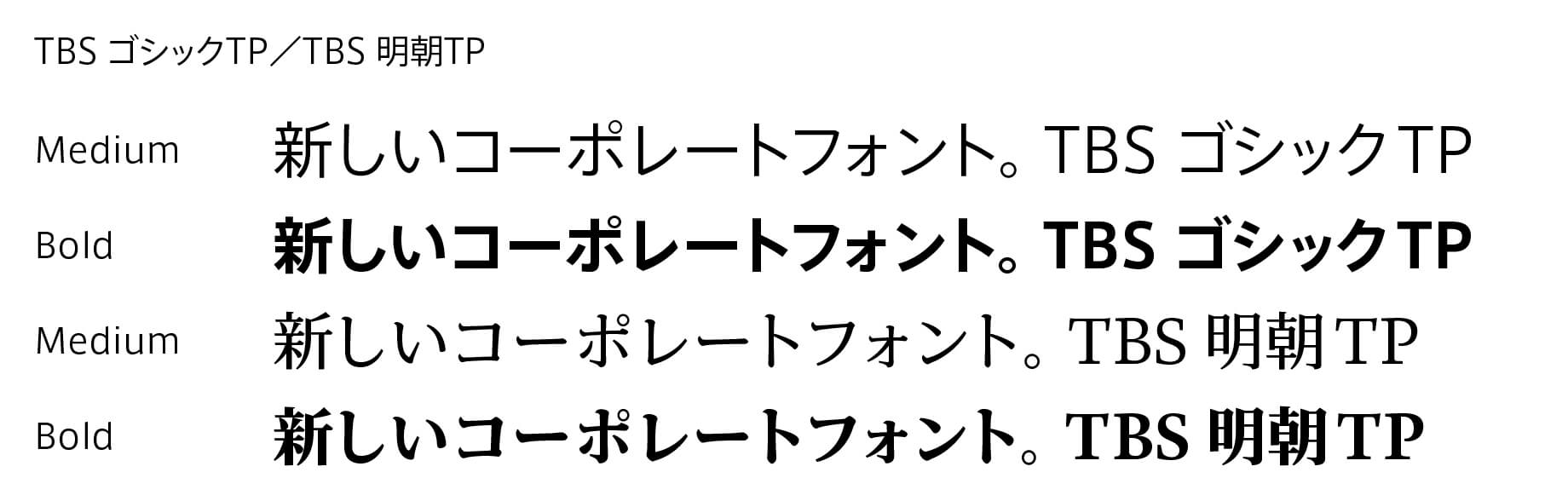
総合プロモーションセンター兼デザインセンターの松原貴明氏は、「TBSでドキュメントを作るときの推奨フォントとしているのですが、その使用が徐々にではありますが増えてきていると実感しています。会社としてコーポレートフォントの導入は初めてなのですが、トーン&マナーを合わせるだけではなく、『フォントを統一することで会社の見え方が変わる』『TBSと名のつくオフィシャルなフォントがあることで、外向きの見え方が統一されていく』など、コーポレートフォントを使うことの意味が理解され始めていると感じています。」と語ります。
コーポレートフォントは、名刺、局内の看板、営業資料、投資家向け冊子などですでに使用が開始されています。また、Webサイトの会社情報ページと社内イントラサイト、ニュース動画配信、そして地上波の報道番組のテロップとしても使用されています。特にテロップでの使用は、デザインの統一感と合わせて、フォント選定というコスト面でも報道局から頼られていると言います。
総合プロモーションセンター部 次長 兼
デザインセンターデザインマネジメント部
松原貴明氏
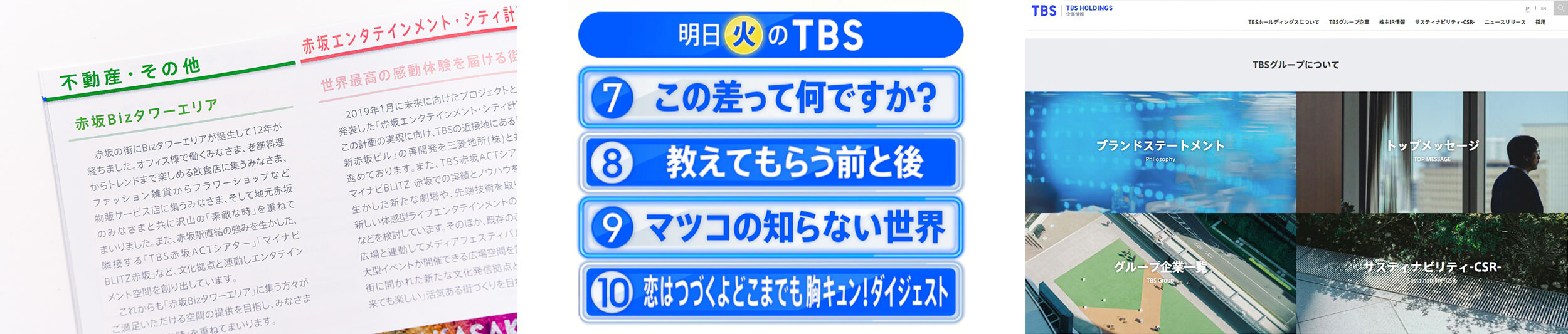
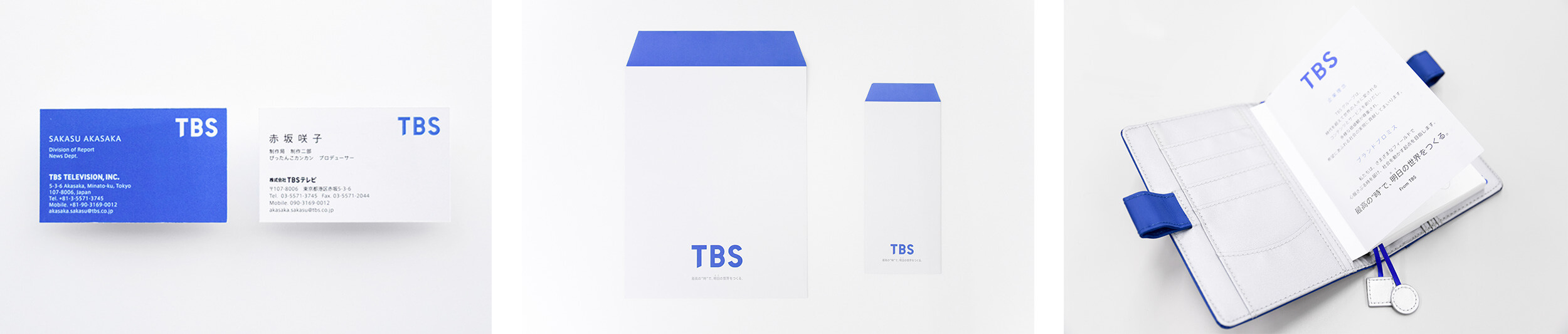
「見え方がより安定してきたということと、書体を毎回選ぶ必要がなくなったことがコスト削減に繋がっています。報道番組は、朝から夜までいろいろな番組があるのですが、フォントによってデザインがバラけてしまうことがよくありました。それが、放送とWebで同じ見え方にできるのは、想定以上の効果です。リブランディングでTBSの青色を規定したこともあって、『ここはTBSのフォントで、TBSの青で』と多くの人が考えるようになり、デザインに対する意識が高まってきたと感じています。想定していた以上に細かなところでコーポレートフォントが使われているのに気づいて、こんなところまで……と感心しています。社内からは、とても読みやすいという声が届いています。」(團野慎太郎氏)
ブランディングフォント
TBSデザインセンターでは、TBSの新しいロゴタイプの仲間となるようなフォントをデザインすること、さらに日本語フォントと組み合わせてブランディング用フォントとして完成させる必要を感じていた際に、フィットフォントと出会ったと言います。
「グループ会社やいろいろなサービスのロゴを同じデザインにしたい、それを誰が作っても同じになるようにしたいと思っていましたので、ロゴを作ることを目的としたオリジナルフォントの開発を考えました。ある講演でタイププロジェクトの話を聞き、オリジナルの欧文フォントが作れるということ、フィットフォントで日本語部分をぴったり合わせてもらえるということを知りました。」(團野慎太郎氏)
原型となるオリジナルデザインの印象を損なわないこと、入力するだけでロゴ作成ができること、そして可読性という機能を備えていることなど、ブランディングフォントの開発にあたりいくつかの条件がありました。日本語部分に関しては、オリジナルの欧文フォントと相性が良いこと、記号類やウエイトが充実していることも重要な点でした。
タイププロジェクトは、欧文フォントを新規開発し、和文部はAXISフィットフォントで最適な数値を設定したブランディングフォント、「TBS Sans TP」の6ウエイトも提供しています。
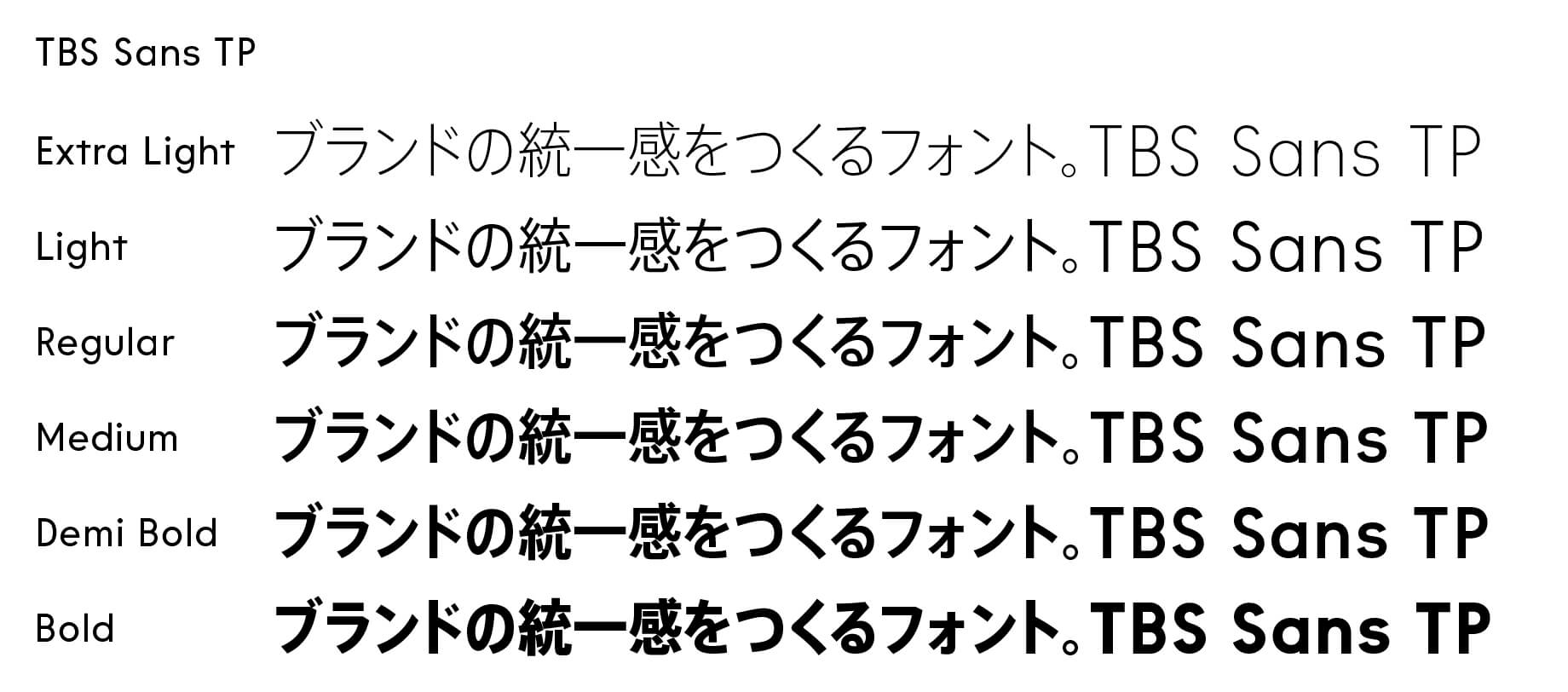
「オリジナル欧文フォントを最初に見た時は、少し驚きました。デザインの原型を渡す時に、ある程度完成しているつもりでしたが、細かいところを修正いただいたことで、フォントとして完成していなかったことに気づきました。実際に使い始めると、入力するだけですぐにロゴとして使える機能性に感動して、何にでも使えるという手応えを感じました。」(團野慎太郎氏)
ブランディングフォントである「TBS Sans TP」は、TBSの新ブランドプロミス「最高の“時”で、明日
の世界を作る」のコピービジュアルを始め、番宣CMやグループ会社や各サービスのロゴなど、あらゆる場面で使用されています。デザイナーチームでは、使用するフォントを検討する必要がなくなったことで、とても効率的に進めることができ、誰が担当してもデザインにブレがないので、TBS Sans TPを使える安心感が大きいと言います。
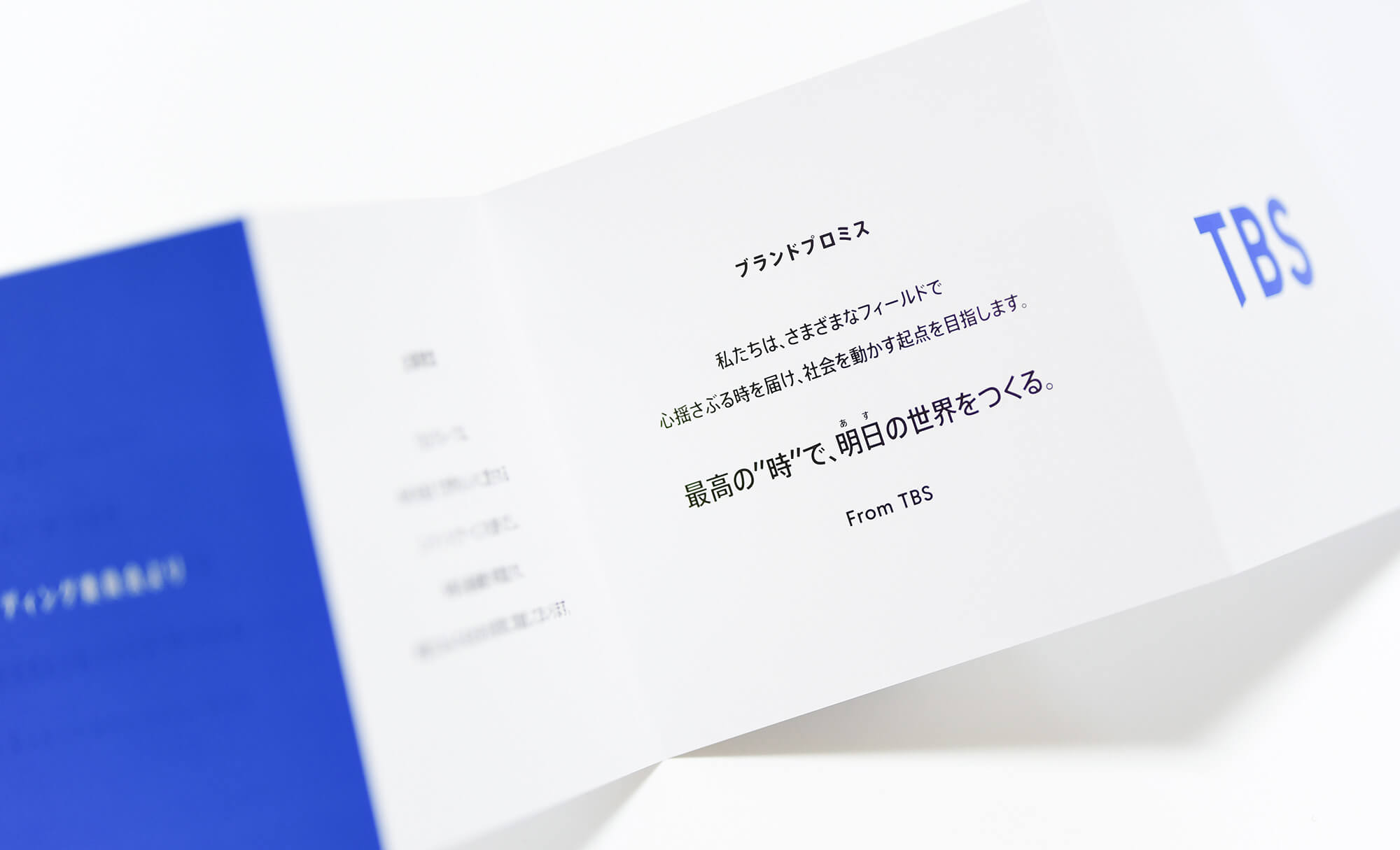
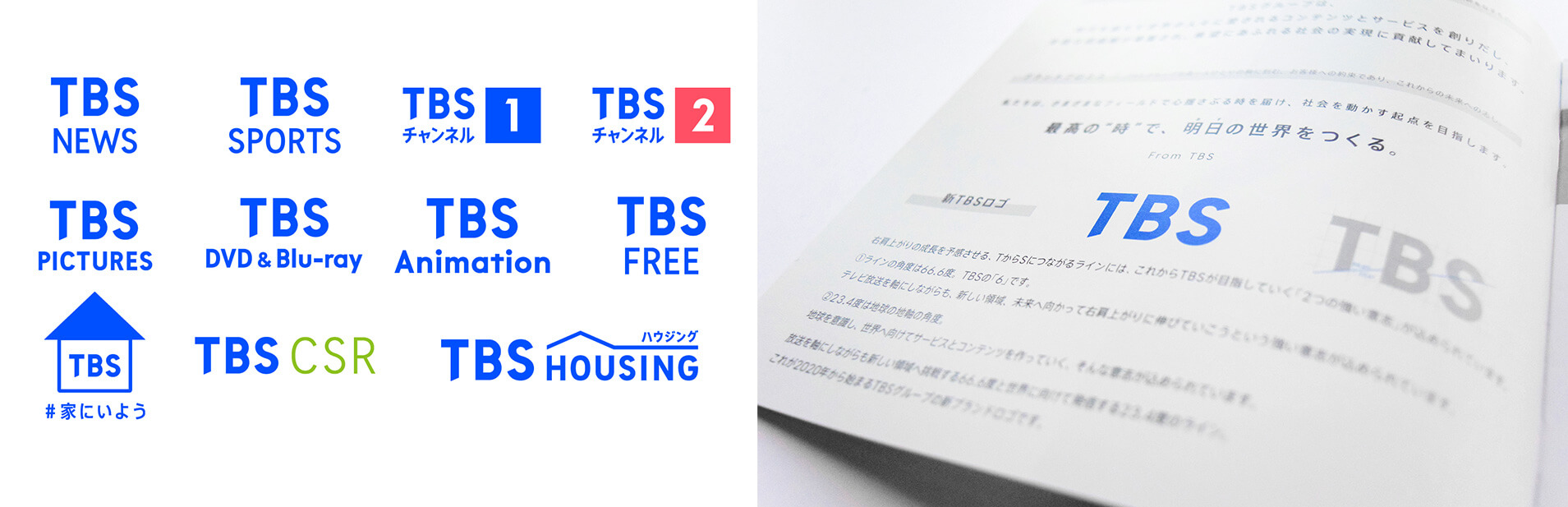
「うまく伝わるか不安ですが、ブランディングフォントが無くては生きられない体になってしまった感じです (笑)。担当者の好みやその時の気分に左右されず、いつ誰が担当しても同じ見え方になるように気をつけているので、毎回、どんなデザインにするか考える時間や、TBSらしさって何だろうと探る必要がなくなりとても効率的です。株主総会などの資料を見た役員にも、『これはTBSのフォントだよね』と認識されるようになっています。コーポレートフォントとブランディングフォントの両方があるからこそ、広く隈なくカバーできると感じています。」(團野慎太郎氏)
「基本的に、見出しなどデザイン要素が必要なところはブランディングフォント、文章や運用をしていくものはコーポレートフォントというすみ分けをしています。コーポレートフォントに関しては引き続き啓蒙が必要だと思っていますが、グループ会社を含めた全社員のパソコンにプリインストールされているのは、会社としては非常に大きな変化です。今までは、自分の好きなフォントを使えばいいと思っていた方々に、コーポレートフォントを導入することの意義や、使うことがとても大事だという認識が少しずつ広がっています。」(松原貴明氏)